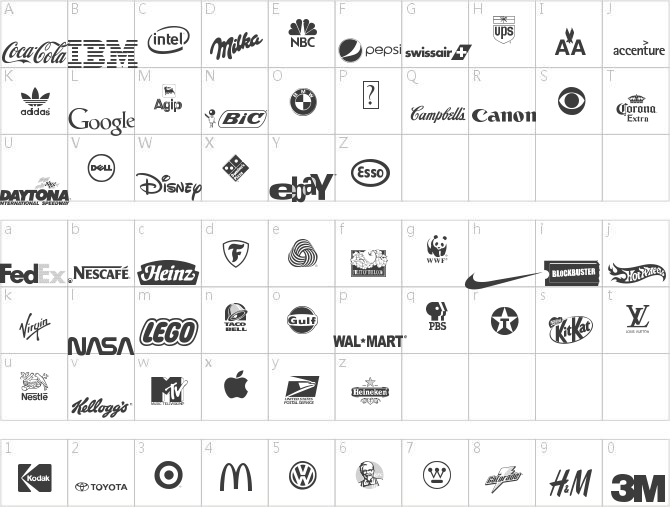
the world's best logos
the world's best logos介绍
the world's best logos字体字库是一款让人赏心悦目、百看不厌的英文字体,适合各类广告和产品包装设计应用,字体大小0.47MB,格式为ttf字体,上传用户是15331803325,作者/版权方为未知